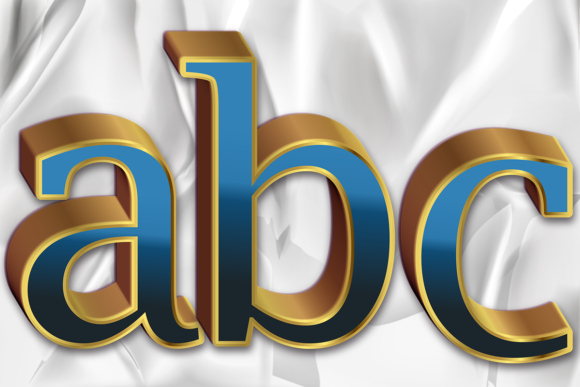
Style Effect Lowercase Letter Number PNG
Việc tìm kiếm các thành phần thiết kế phù hợp có thể là một thách thức, nhưng Style Effect Lowercase Letter Number PNG cung cấp một bộ sưu tập đặc biệt giúp nâng tầm công việc của bạn ngay lập tức.
Được chế tác với độ chính xác cao, Style Effect Lowercase Letter Number PNG cung cấp các vector sạch, kiểu chữ mượt mà và giấy phép thương mại để bạn yên tâm.